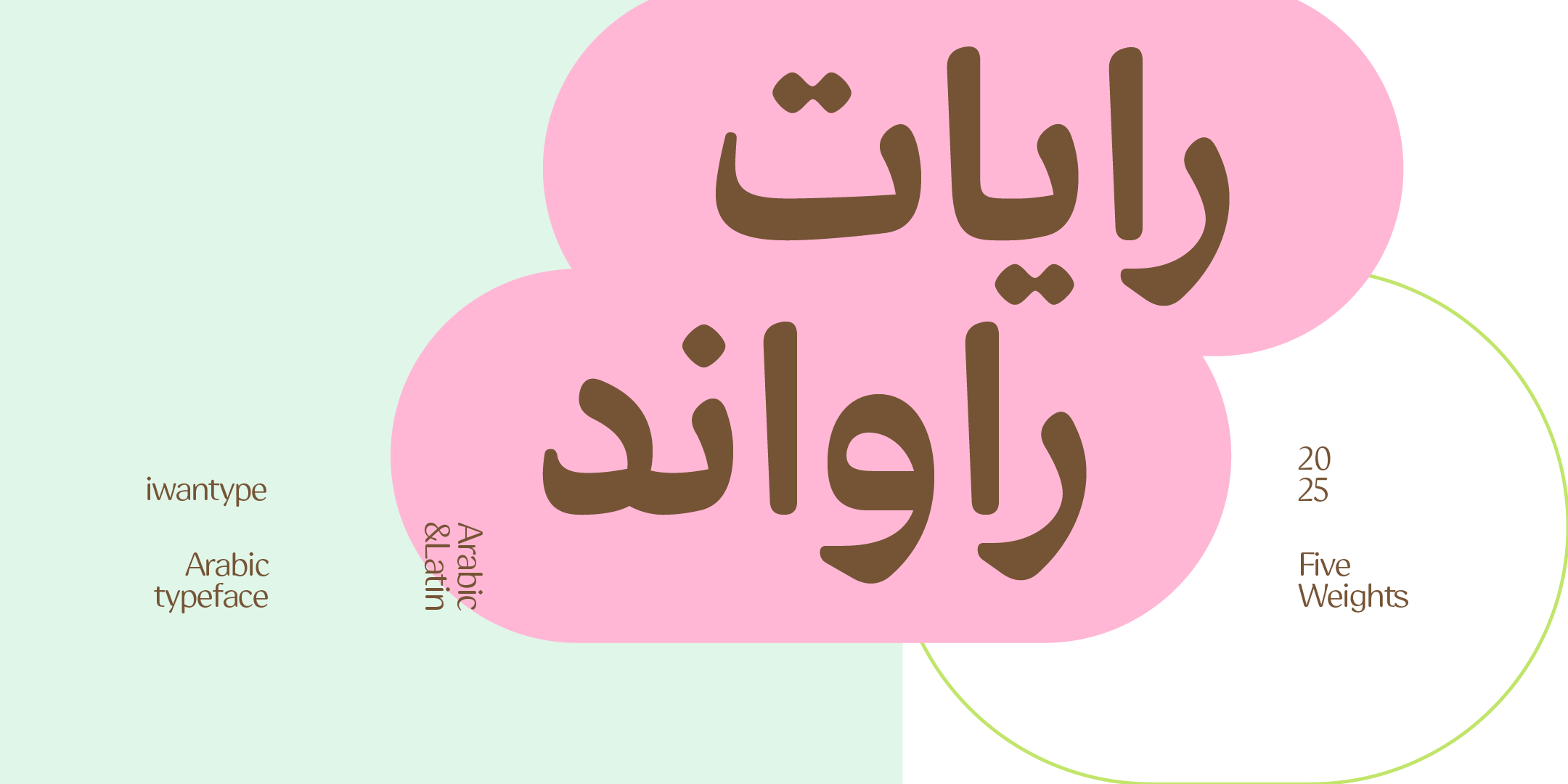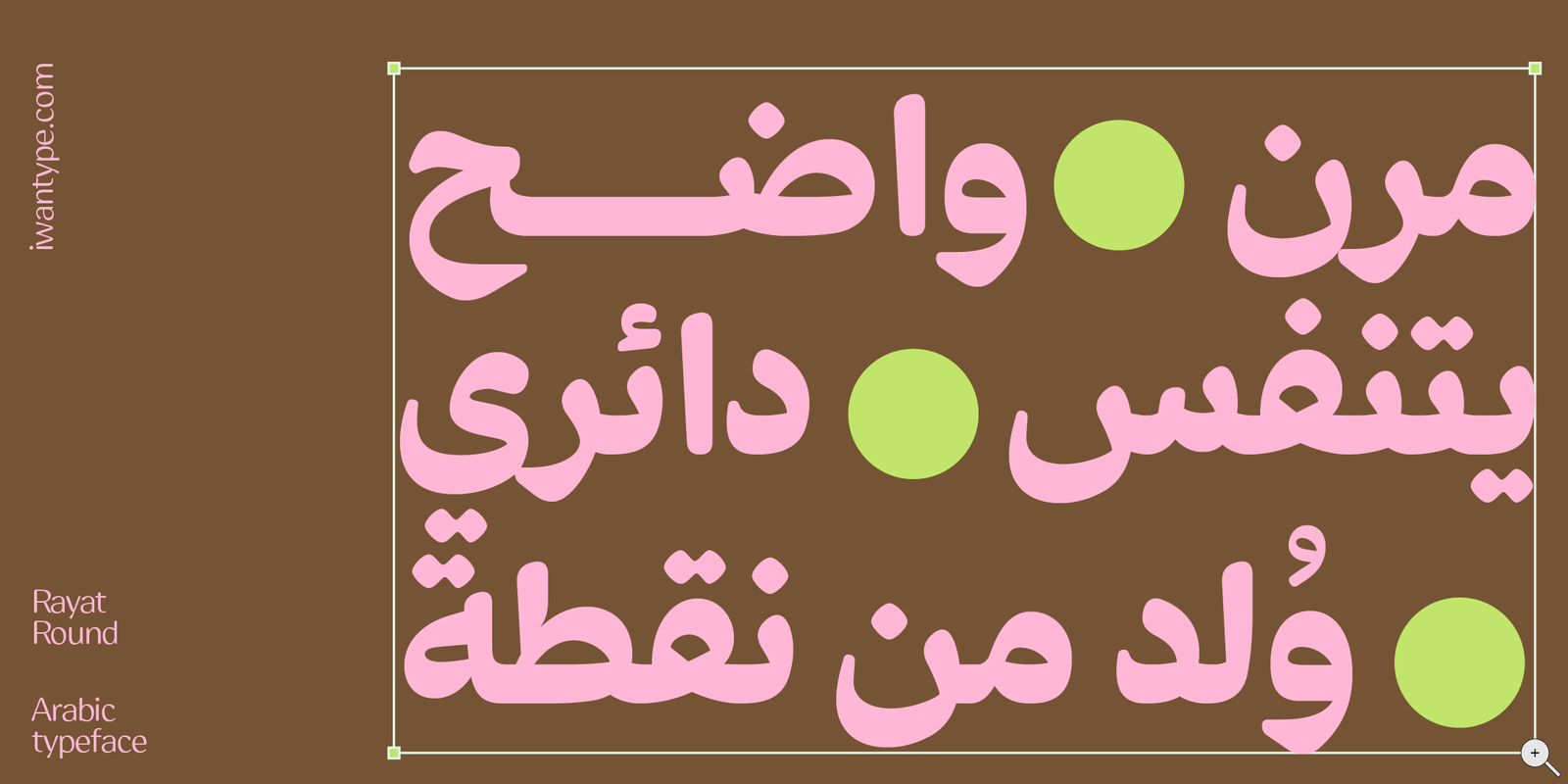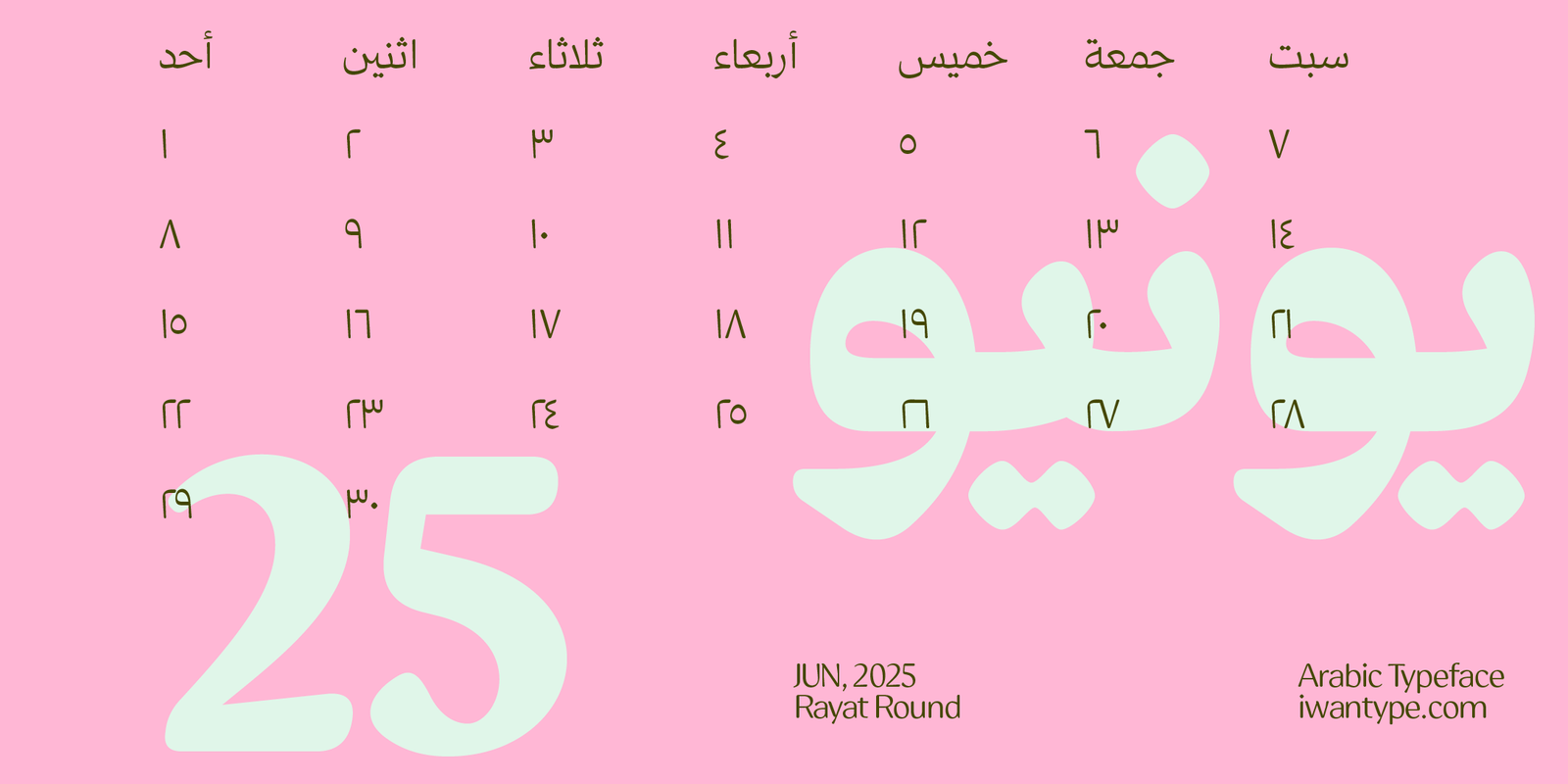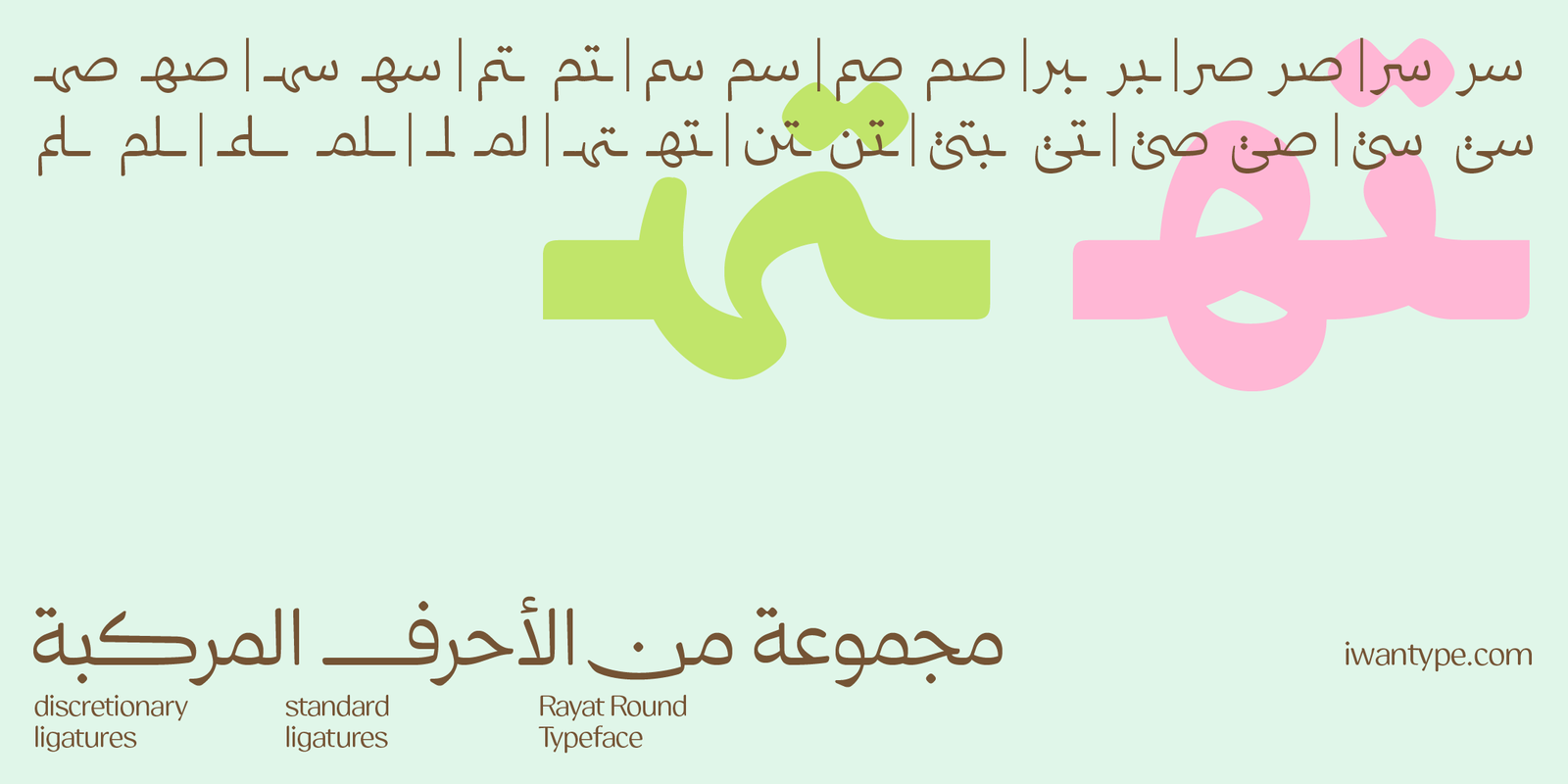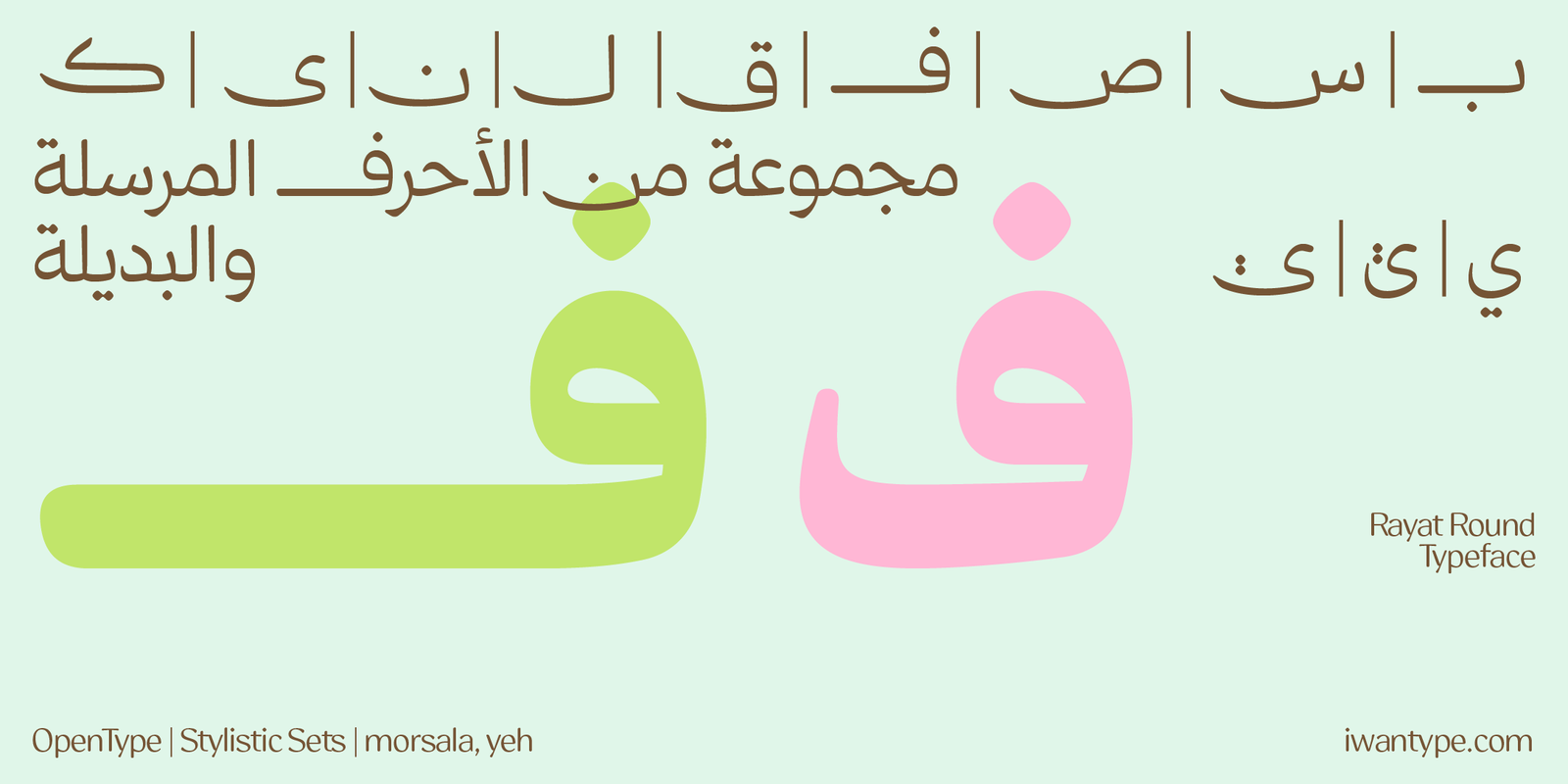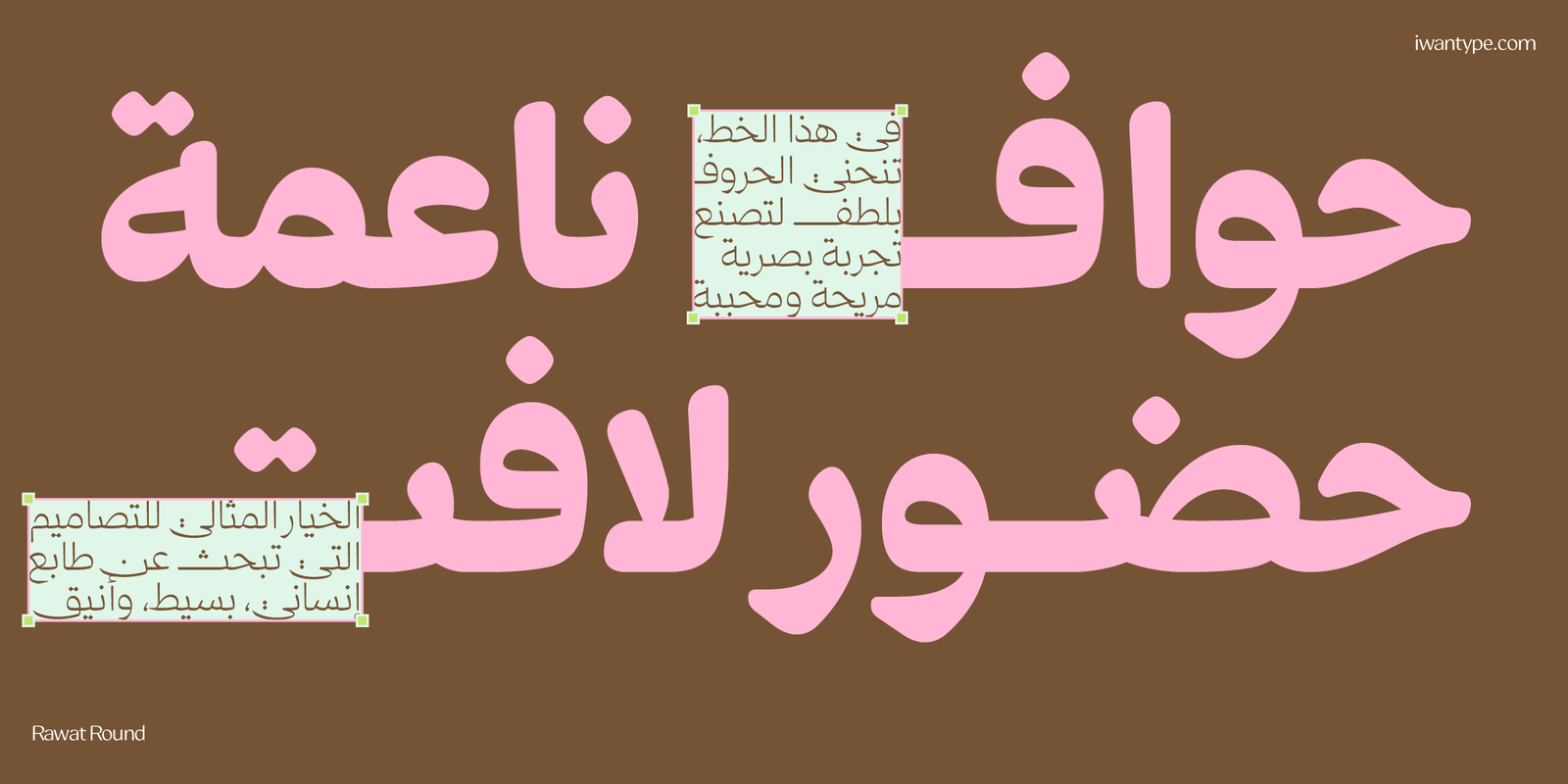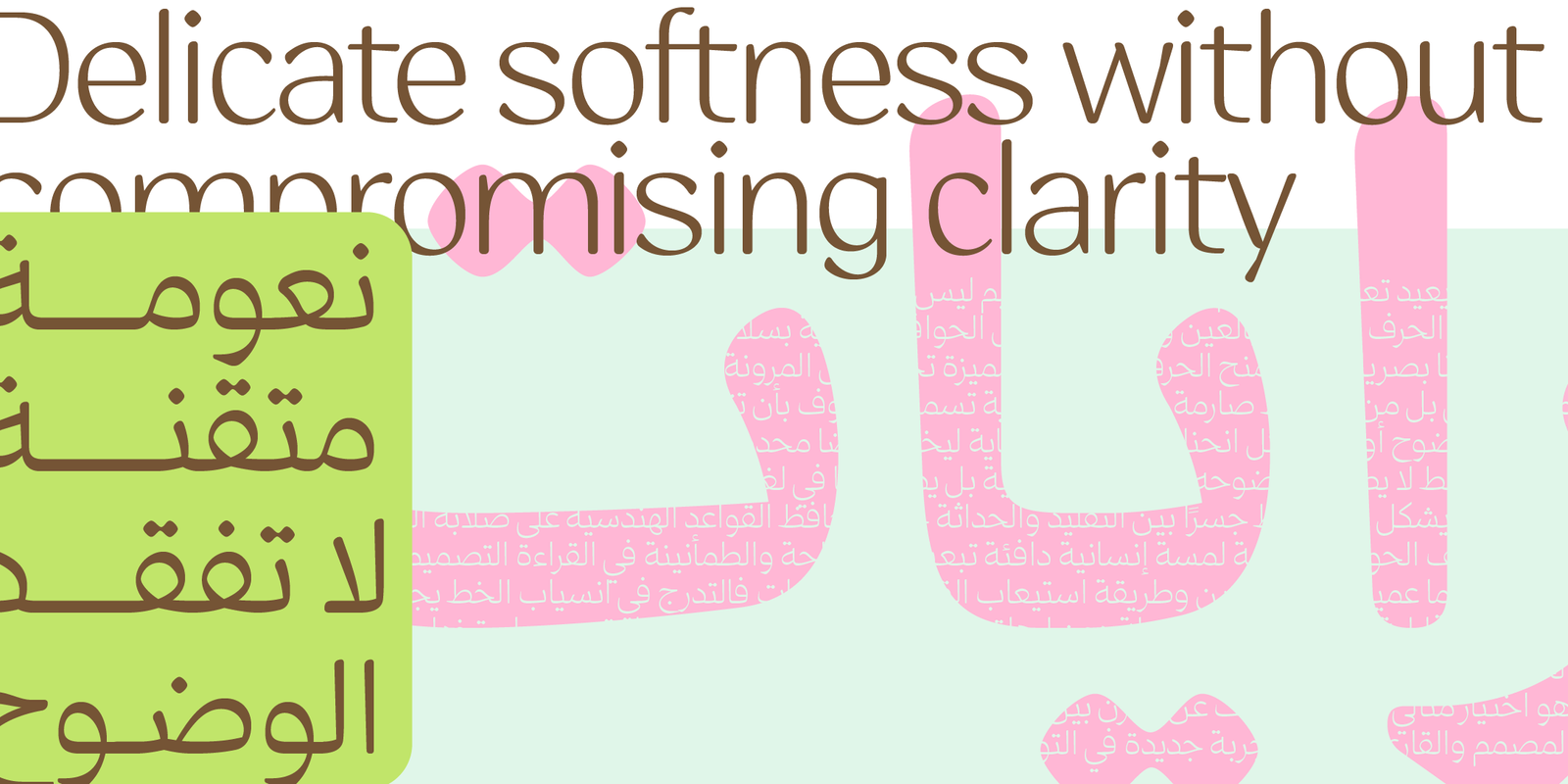
خط رايات راوند – خط نسخ – Rayat round typeface
رايات راوند هو امتداد جديد لعائلة خط رايات، يتميّز بنهايات دائرية ناعمة تضيف طابعًا إنسانيًا ودودًا إلى البنية الهندسية الصارمة للخط الأصلي.
حافظ الخط على وضوحه واتزانه، لكنه جاء بنعومة تجعل منه خيارًا مثاليًا للمشاريع المعاصرة التي تستهدف جمهورًا أوسع أو تحمل طابعًا بصريًا مرنًا ومحببًا.
مميزات خط رايات الطباعي:
- مزايـا OpenType: يتضمن الخط العديد من مزايا OpenType التي تضفي عليه مرونة وتنوعًا في الاستخدام، مثل:
- الحروف المرسلة: لمسة تقليدية تضفي على النصوص جمالية خاصة.
- حرف ياء بنزول أقل: يقلل من نزول السطر، مما يعزز من انتظام النصوص.
- النقطات البديلة: توفر تنوعًا وجاذبية بصرية إضافية للنصوص.
- الحروف المركبة: تسهم في تحسين المظهر العام للنص وتزيد من سلاسته.
- توافر الأوزان: يأتي خط رايات الطباعي بخمسة أوزان مختلفة.